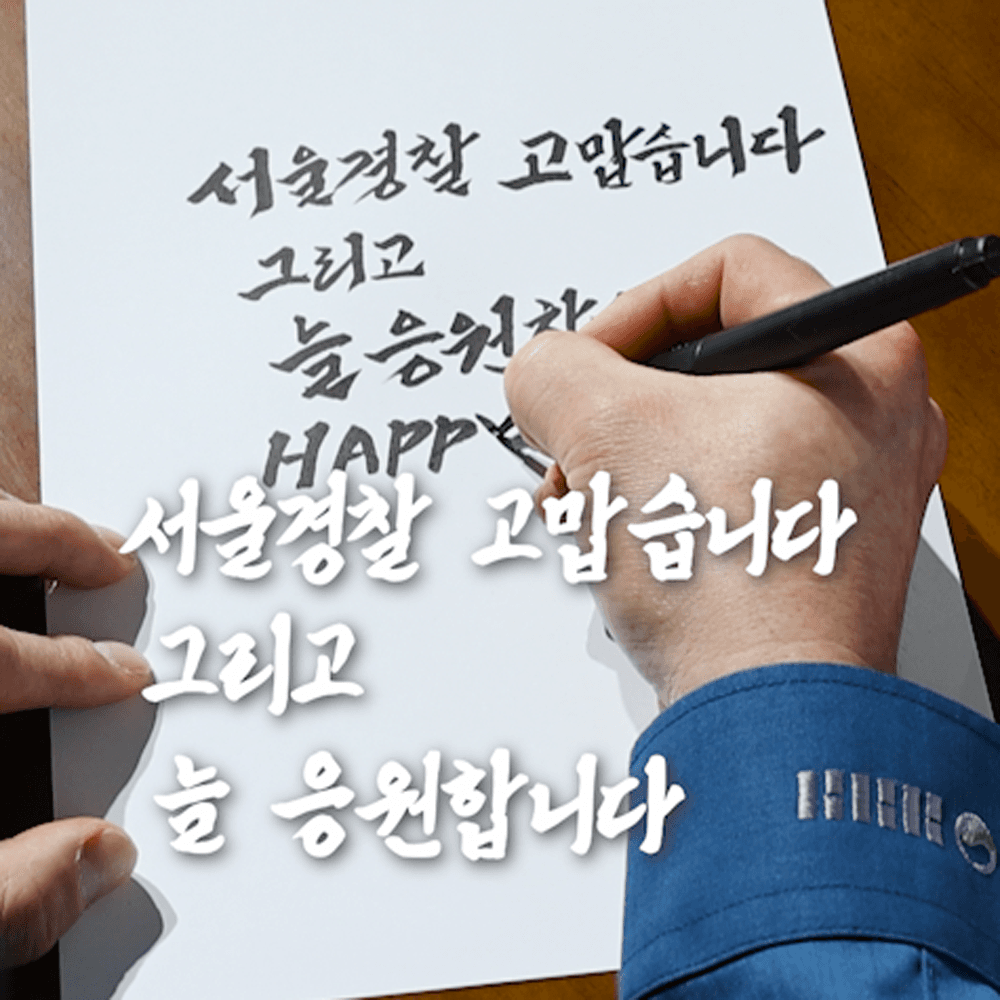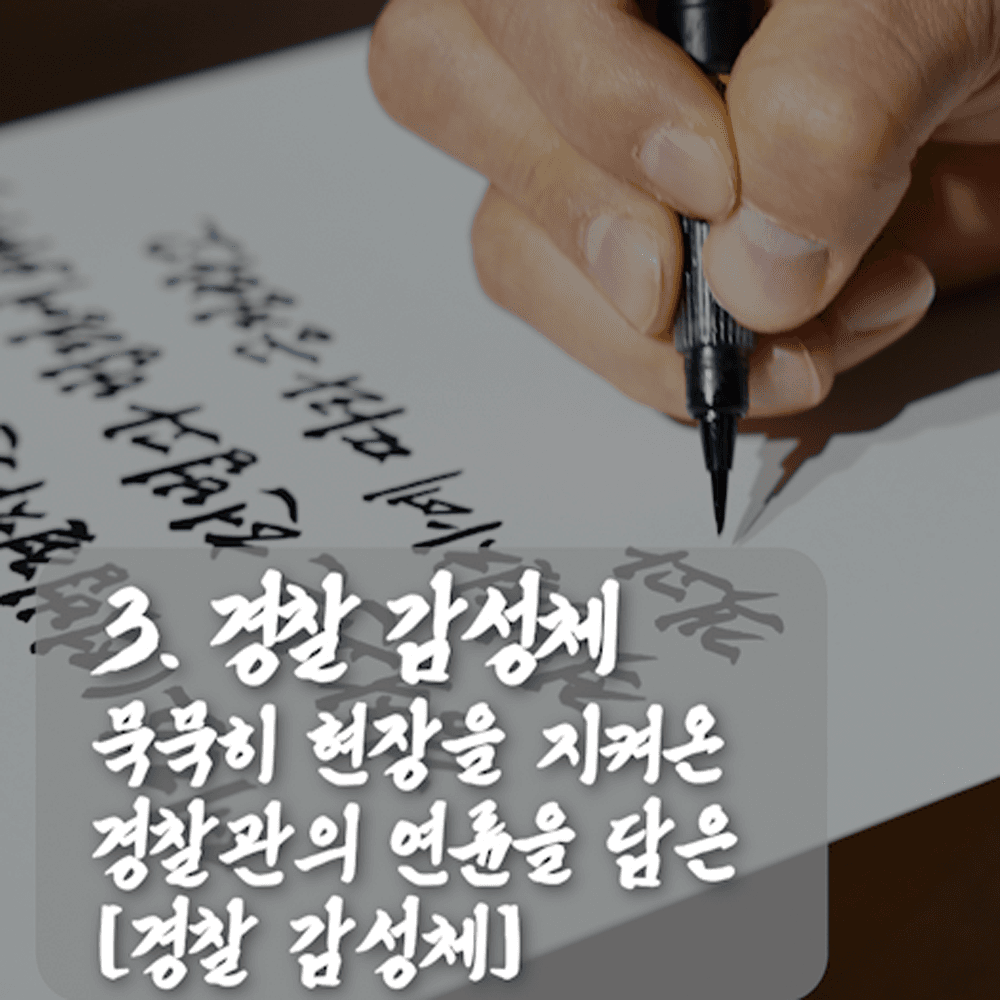
그리운 경찰감성체
Griun PolSensibility
그리운 경찰감성체 소개
‘그리운 경찰감성체’는 서로 다름을 이해하고, 차별과 혐오를 넘어선 공감대 형성을 통한 공존의 세상으로 나아가기 위한 바람으로 제작되었습니다. 서울경찰 「인권손글씨 공모전」에 수상작으로 선정된 경찰감성체는 자유와 연대를 향해 거리낌 없이 써 내려간 시원한 느낌의 필체인데요, 정성과 공감치안을 향해 뻗어가는 구석구석의 노력이 우리 모두의 인권감수성을 향상시키고, 사랑과 관심이 깃든 사회로 발돋움하기 위해 널리 사용되어지길 꿈꾸어봅니다.